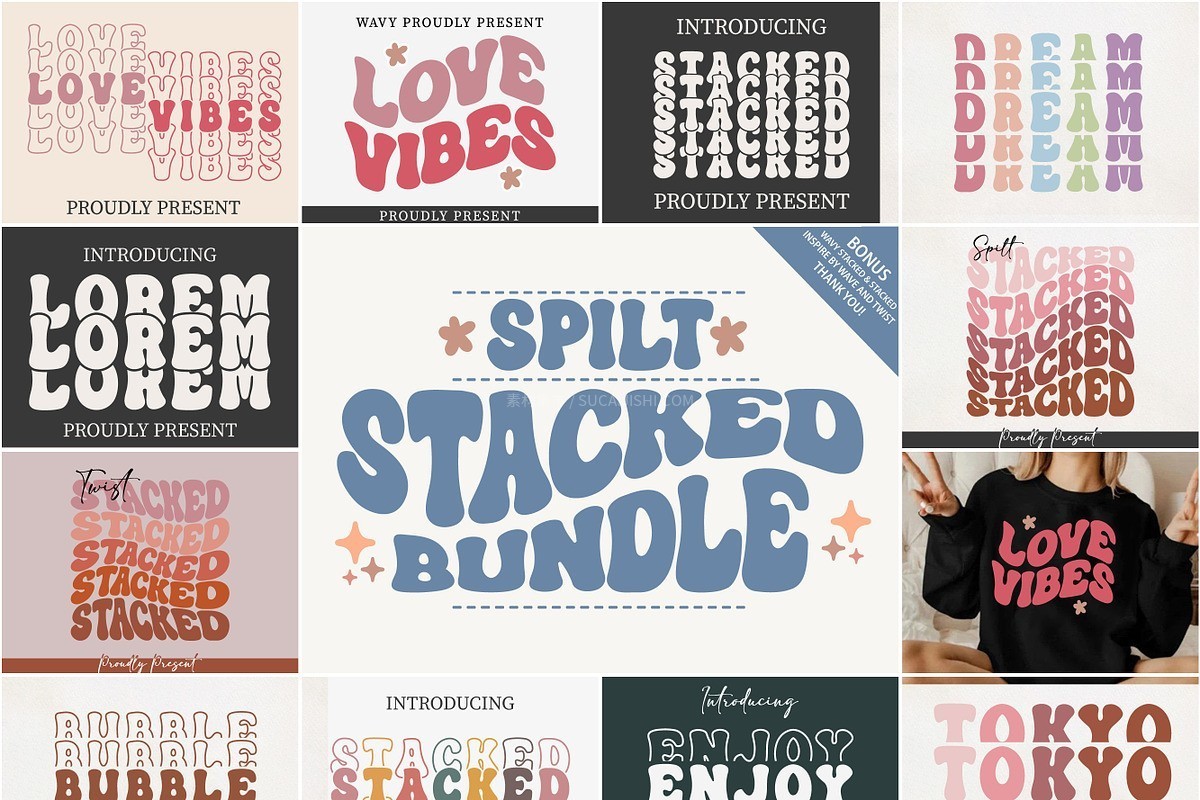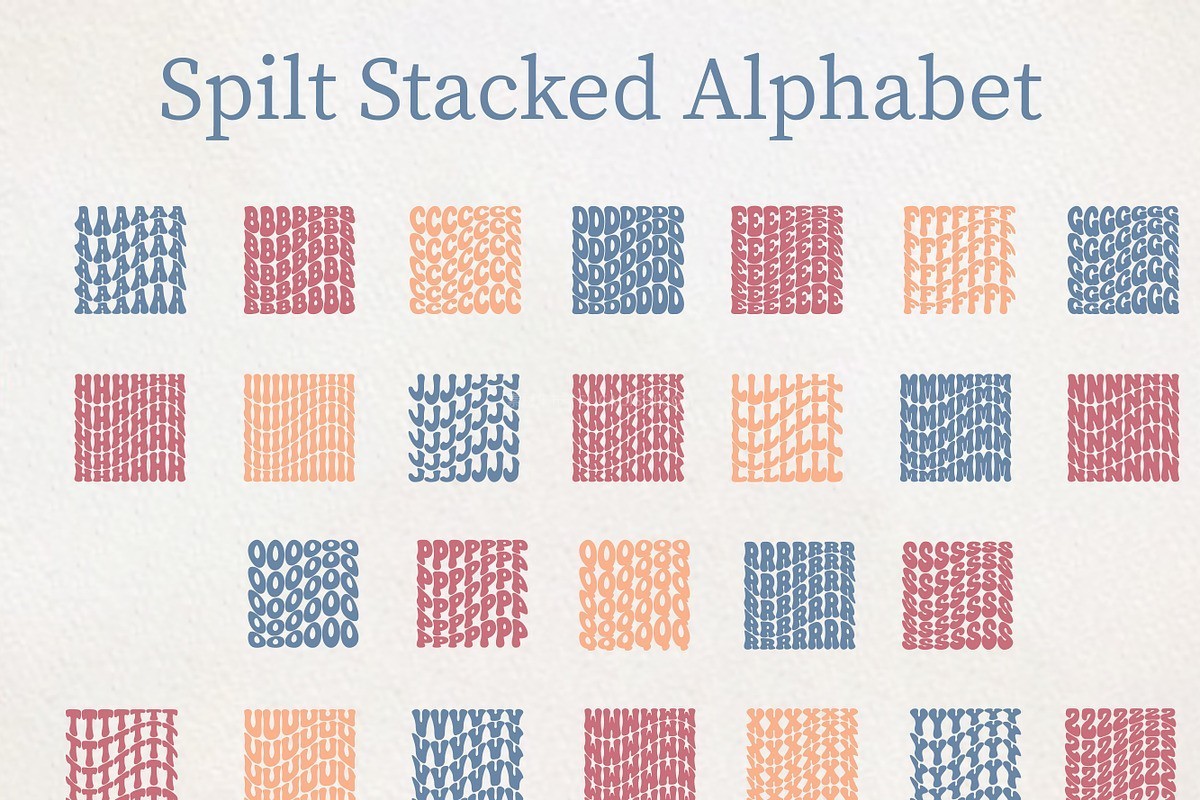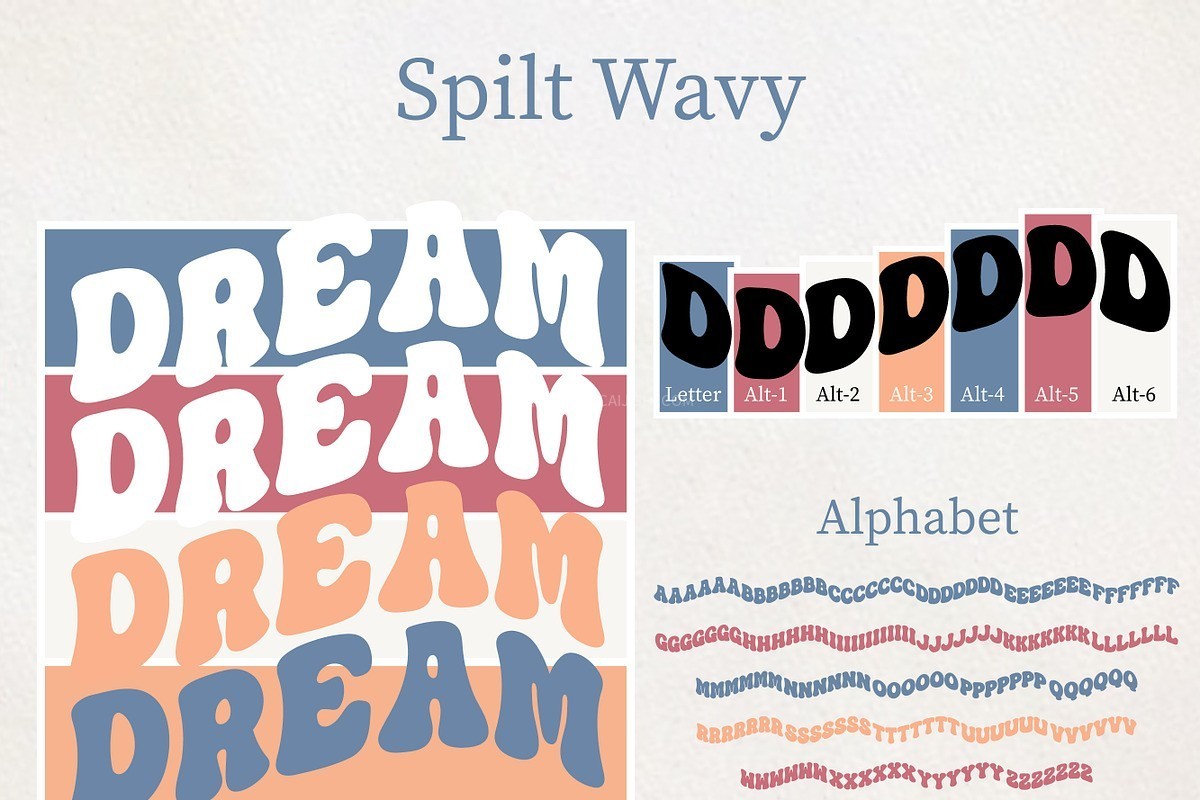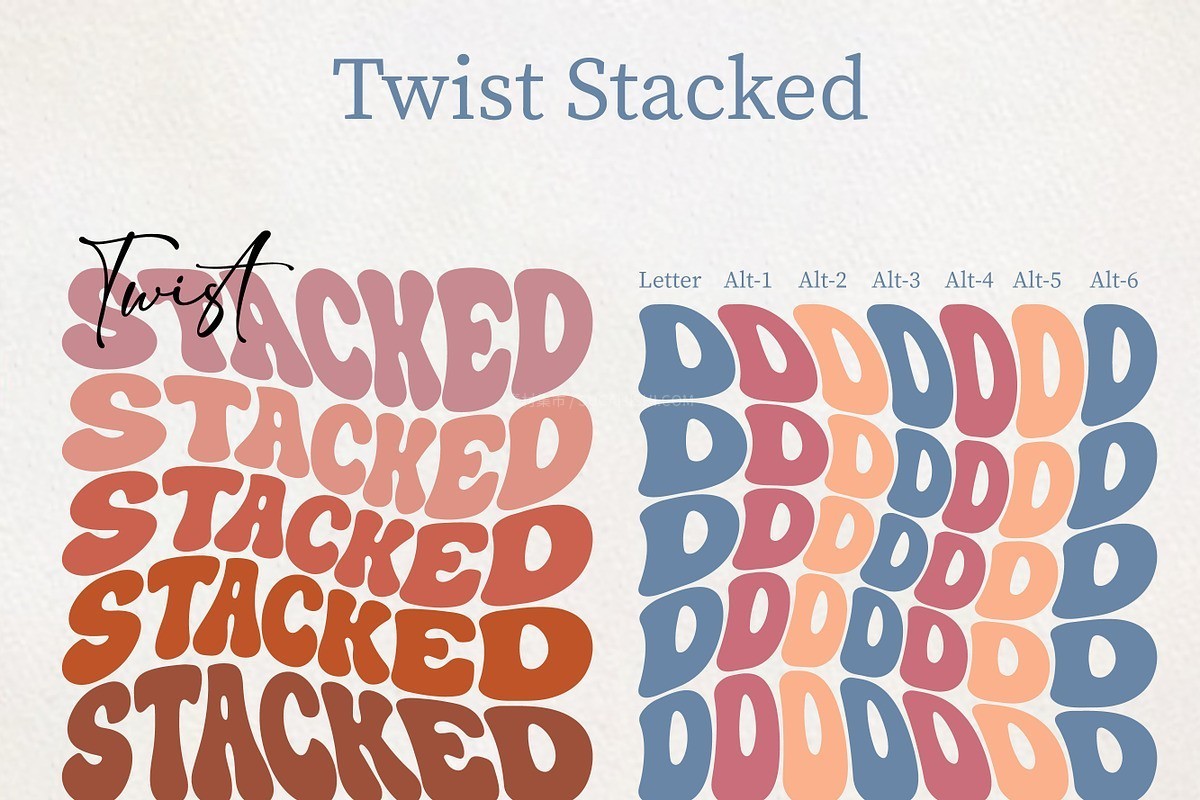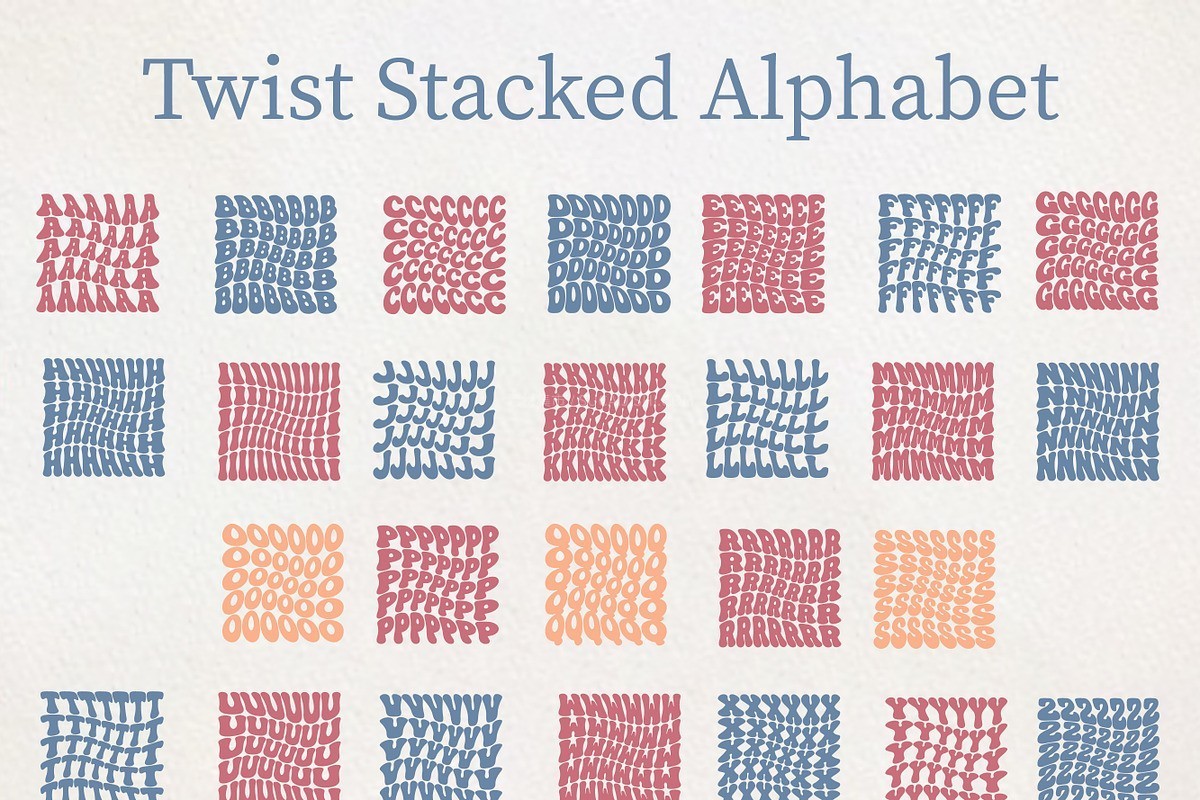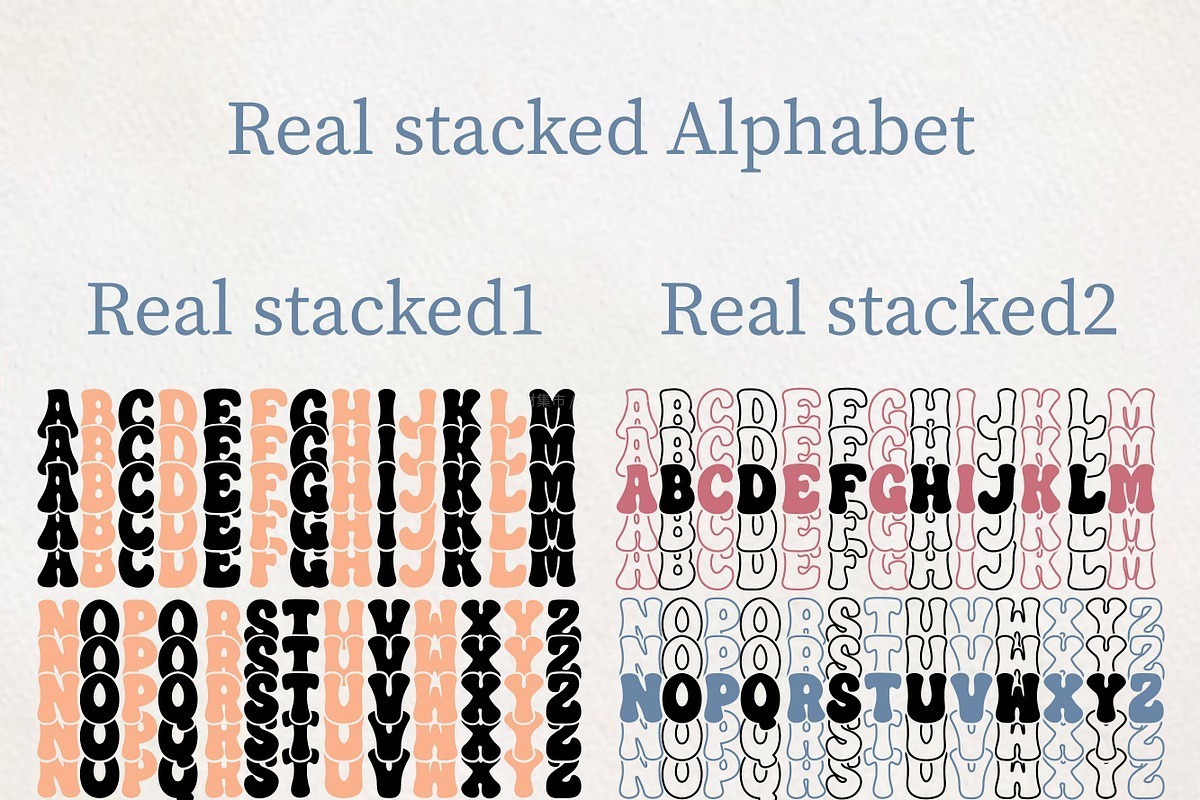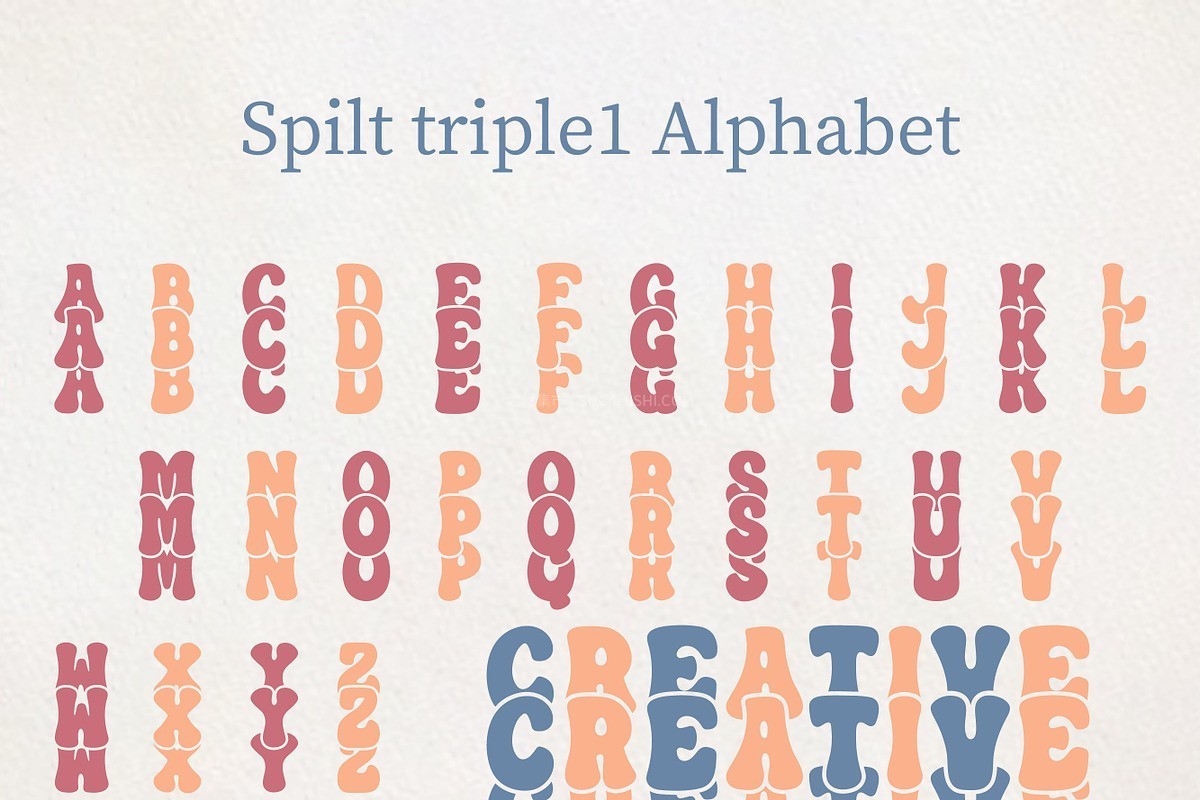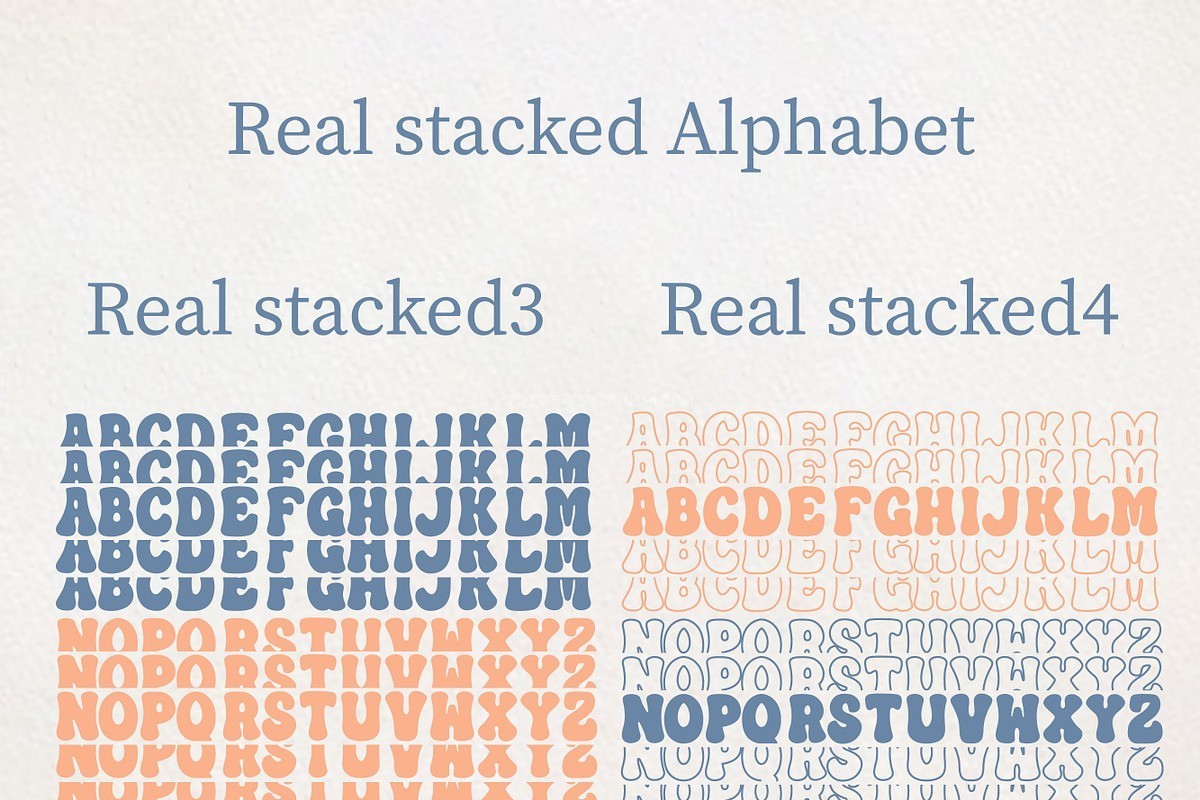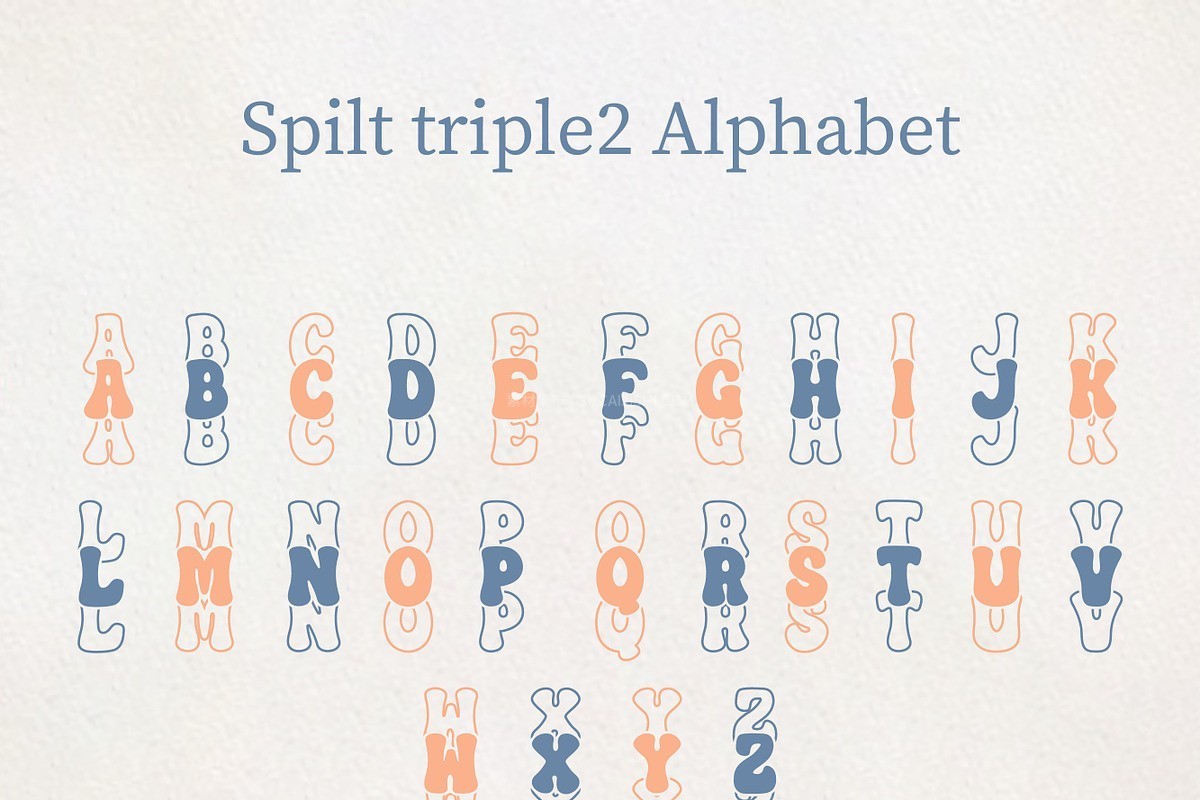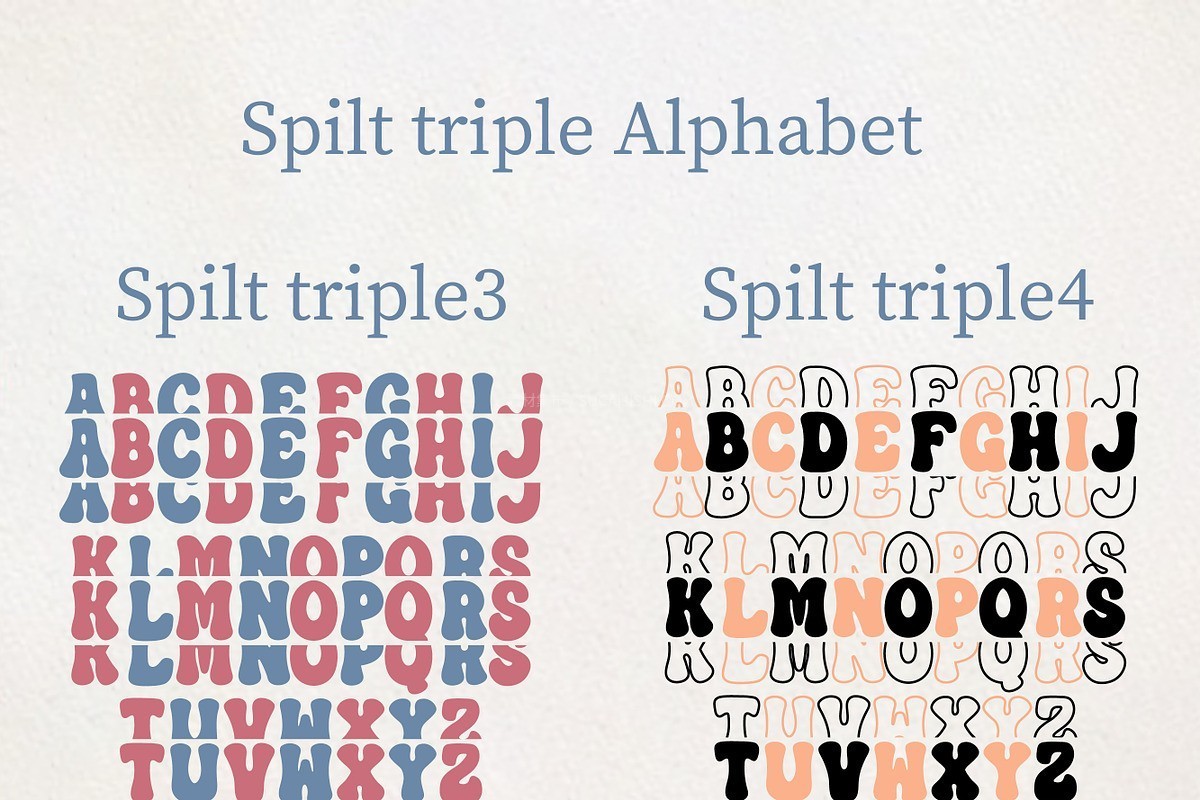
Spilt Stacked Bundle:11款创意堆叠效果装饰字体
这款 Spilt Stacked Bundle 自带超级吸睛的创意堆叠效果,一共包含 11 款不同的字体风格。其中特别亮眼的 Wavy 是一款超酷的展示字体,内置丰富的替代字形,能帮你轻松拿捏时尚又个性的自定义排版。整体风格可爱满分、趣味十足,百搭又好用,绝对是给作品增添活力与视觉焦点的绝佳选择!
Windows 渲染这字体发虚,但在 Mac 视网膜屏上惊艳得不行,屏幕渲染差异太坑了。